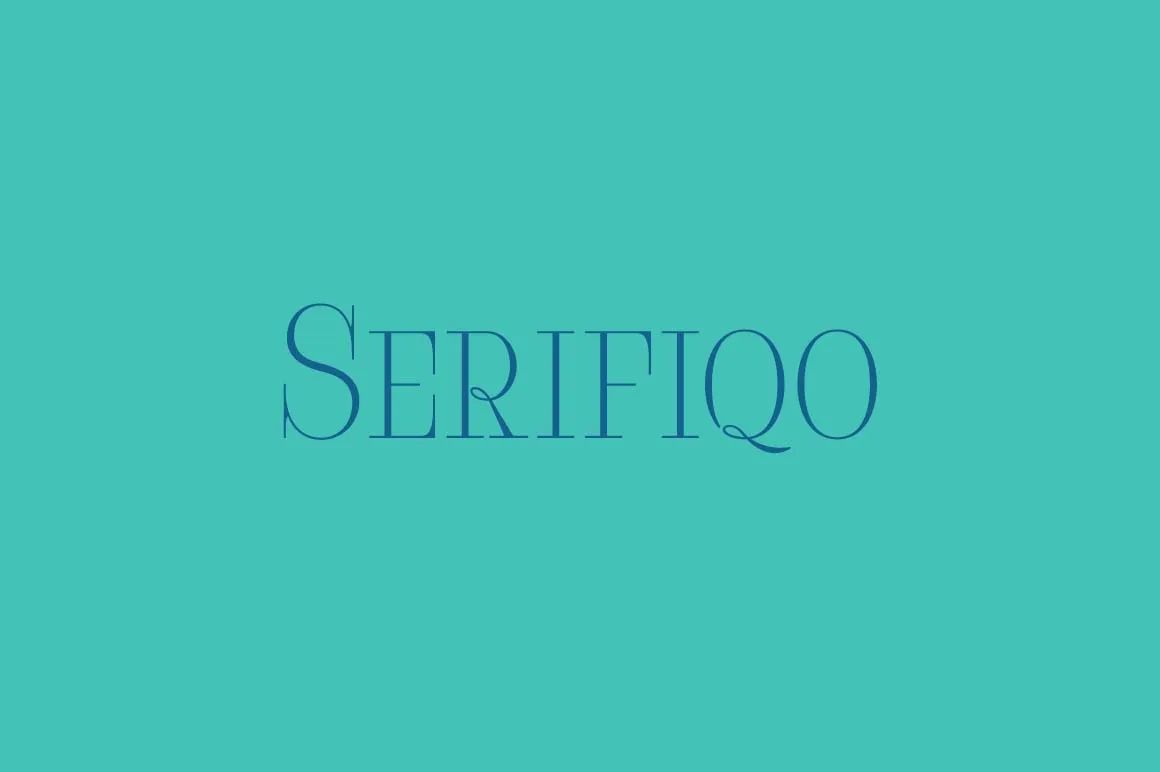
A fonte “Serifiqo Font” traz uma atmosfera claramente vintage, envolvida por linhas redondas e detalhes trabalhados que remetem a um tempo distante do design de tipografia serifa. Ela foi criada pelo designer Hamilton e tem origens no trabalho de Sergiy Tkachenko. Esta fonte é perfeitamente adequada para aplicativos como rótulos de embalagens antiguinadas, encadernações escolares, ou até mesmo gráficos históricos, oferecendo um toque nostálgico e sofisticado que se encaixa perfeitamente em qualquer design. Se você está procurando por uma fonte vintage para seus projetos, “Serifiqo Font” é uma excelente opção para adicionar profundidade e elegância a seu trabalho de design. Não perca esta oportunidade de reviver um tempo passado através das letras.